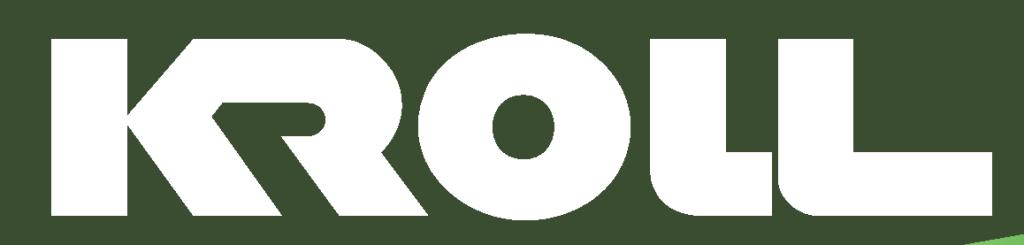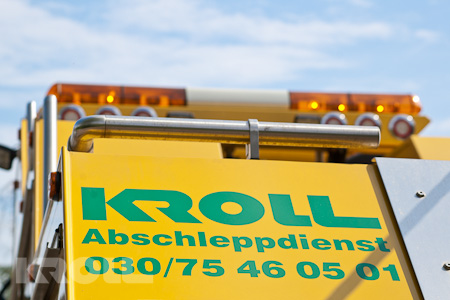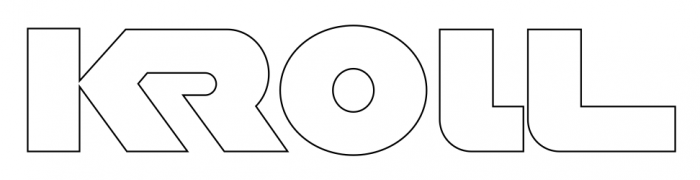
Suche Firmen Logo Schrift mit verbundenen Buchstaben "KR" und zwei verschiedenen "L" Buchstaben
wir suchen die Schriftart von unserem Firmen Logo. Wir sind uns nicht einmal sicher, ob es überhaupt eine Schriftart ist bzw. diese selbst gezeichnet  / entworfen wurde.
Markante Merkmale: der Buchstabe K und R sind miteinander verbunden. Die beiden "L" Buchstaben haben unterschiedliche Schenkel Längen.
Eventuell hat jemanden einen Tipp / Hinweis von euch.
Zur Frage: Mit an Sicherheit grenzender Wahrscheinlichkeit gibt es das so in dieser Form nicht als Satzschrift. Ein Grafiker zeichnet das aber binnen kurzer Zeit problemlos nach, falls es um die Erstellung neuer Vorlagen gehen sollte.
Hat zwar mit der Ursprungsfrage eigentlich nichts zu tun (Antwort: es ist keine Satzschrift, sondern ein handgemachter Schriftzug eines Grafikers), aber betreffs Markeneintrag würde ich mir in diesem Fall keine Sorgen machen – das ist keine Pflicht, sondern nur ein rechtlicher Schutz für den Markeninhaber gegen Trittbrettfahrer, der in diesem Fall wirklich wenig Sinn macht und Geld kostet – vermutlich wurde das damals aus genau dem Grund gekündigt.
Ja das ist Richtig, es geht uns um eine ordentliche Satzschrift Vorlage. Die Quelle ist leider versiebt und wir stehen immer wieder vor dem Problem das wir keine ordentliche Vorlage haben z.B. für Druckereien usw..
PS. Ich denke auch, das wir uns eine neue Satzschrift Vorlage erstellen lassen müssen.
Also statt "Firmen Logo Schrift" besser "Firmenlogoschrift" oder "Firmenlogo-Schrift" und statt "Satzschrift Vorlage" besser "Satzschrift-Vorlage"
So viel zur Rechtschreibung. Zur Vorlage: Hier gibt es mit Garantie keine Satzschrift, die man leicht abgewandelt zum Logo umbauebn könnte, was auch überhaupt nicht erforderlich ist, denn ich habe mal eben das Logo in genau 8 Minuten nachgezeichnet, da haben wir hier mit all dem Drumherum weit mehr Zeit vertan.
Hier die Outlines des Logos, das ich gegen ein angemessenes Salär gern zur Verfügung stelle:
post-22079-0-98244300-1461332615_thumb.p
Die Outline ihres Logos werden sie haben, schließlich sind deren Fahrzeuge feinsäuberlich damit gebrandet.
Kroll_sm_46.jpg
Eine entsprechende Satzschrift, aus der man das Logo "einfach setzen" kann, wird es nicht geben.
Unser Fließbandfontschmied catfonts stellt seine Outline garantiert auch als Font zur Verfügung.¹²
1. für eine moderate Anzahl von
Wäre der Einsatz eines solchen Logofonts im Text aus gestalterischer Sicht sinnvoll? Ich hab da meine Zweifel …
@ Kroll Spedition: Verrätst du uns, was genau ihr sucht – eine Satzschrift mit genau diesen Buchstaben (wird es nicht geben) oder die Vektordaten des Logos (sollte euer Fahrzeugbeschrifter haben) oder  … ?
Ich mach jetzt hier zu. Die Schriftanfrage ist ja beantwortet (»Es ist keine Satzschrift«).